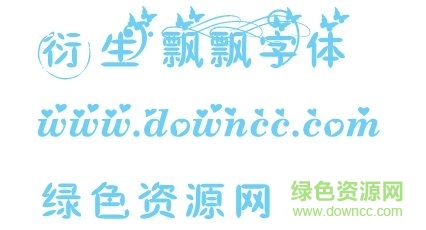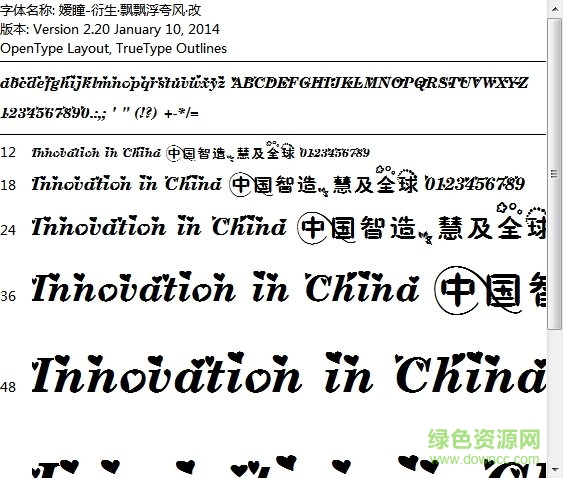
洐生飄飄字體是媛瞳-衍生修改過的飄飄浮夸風字體,添加了超多可愛的點綴和修飾,讓文字盡顯藝術(shù)字體的優(yōu)美視覺呈現(xiàn),十分悅目,很能贏得讀者的好感,快來綠色資源網(wǎng)試試吧!
媛瞳-衍生飄飄浮夸風字體,字體行間增加了心形、花朵、綠葉、圓圈等多種點綴,英文書寫十分流暢和諧,中文簡練而醒目,讓文字呈現(xiàn)出書畫般的唯美效果,倘若你喜歡,來本站下載收藏吧!
飄飄字體是一款能給人超多驚喜的藝術(shù)字體,兼具卡通字體和涂鴉字體的風格韻味,可愛生動的點綴讓你的每個文字都充滿了活力,讓你的手機字體也更具個性特色,同時也可以運用在平面設(shè)計、包裝設(shè)計、藝術(shù)設(shè)計等場合。